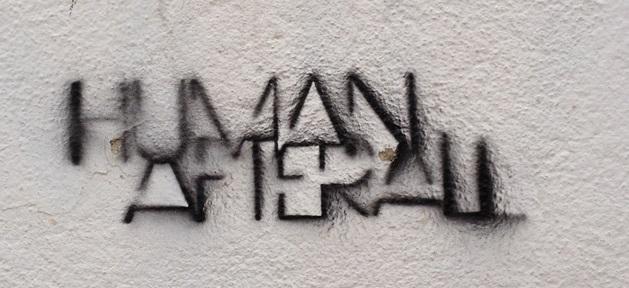
Vielen Dank für eure Antworten! - Mir ist schon klar, dass die Schrift auf meinem Beispielbild gesprayed ist, aber ich vermute doch, dass das ursprüngliche Vorbild für die Fonts nicht gesprayed war. Naja, vielleicht ist's ja auch eine Eigenkreation. Die Fotografie wurde in der Vorstadt in der Nähe von Lissabon gemacht...
Aber eure Tips gefallen mir schon mal nicht schlecht. Vielleicht hat ja noch jemand was, das dem Original noch etwas näher kommt? :-)